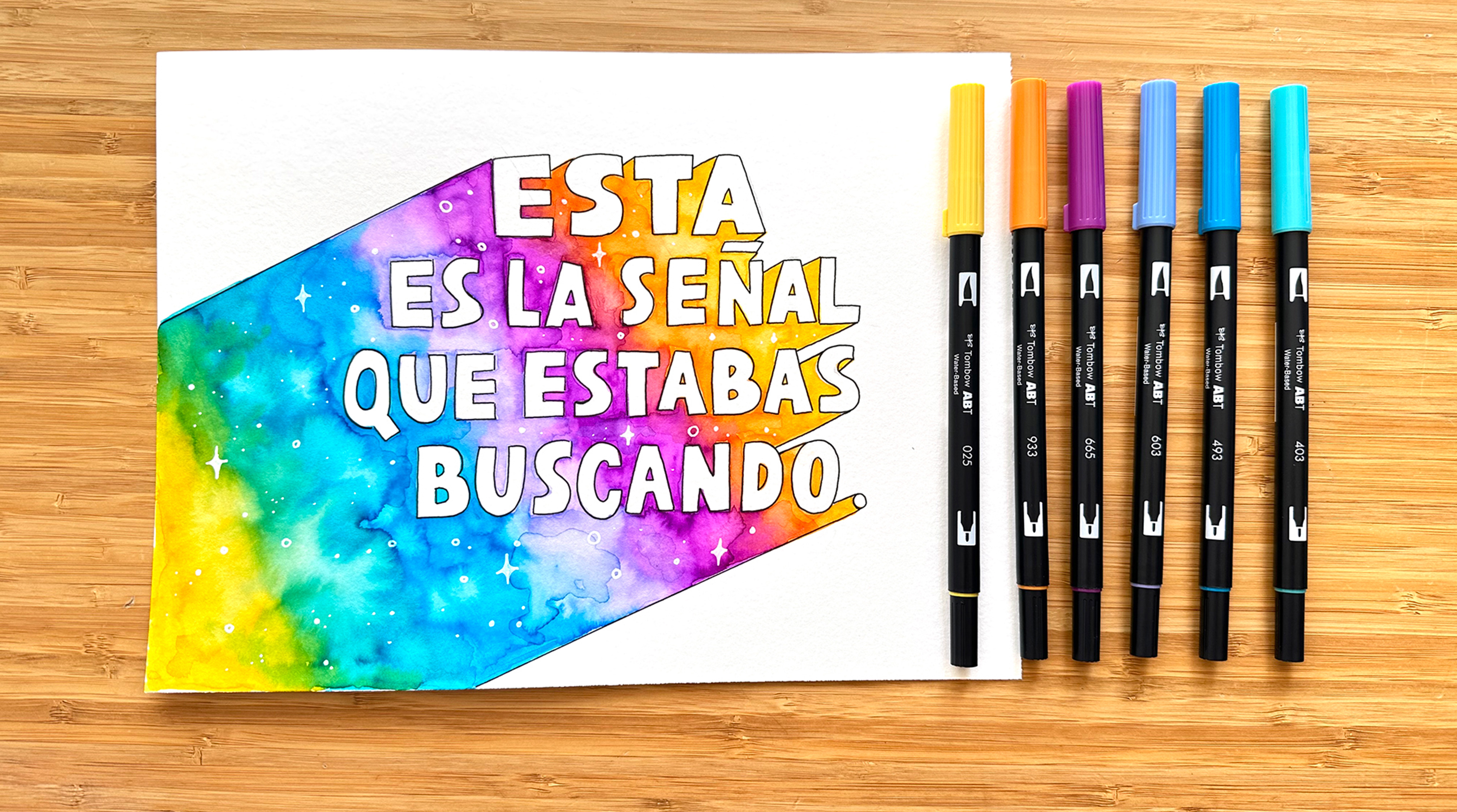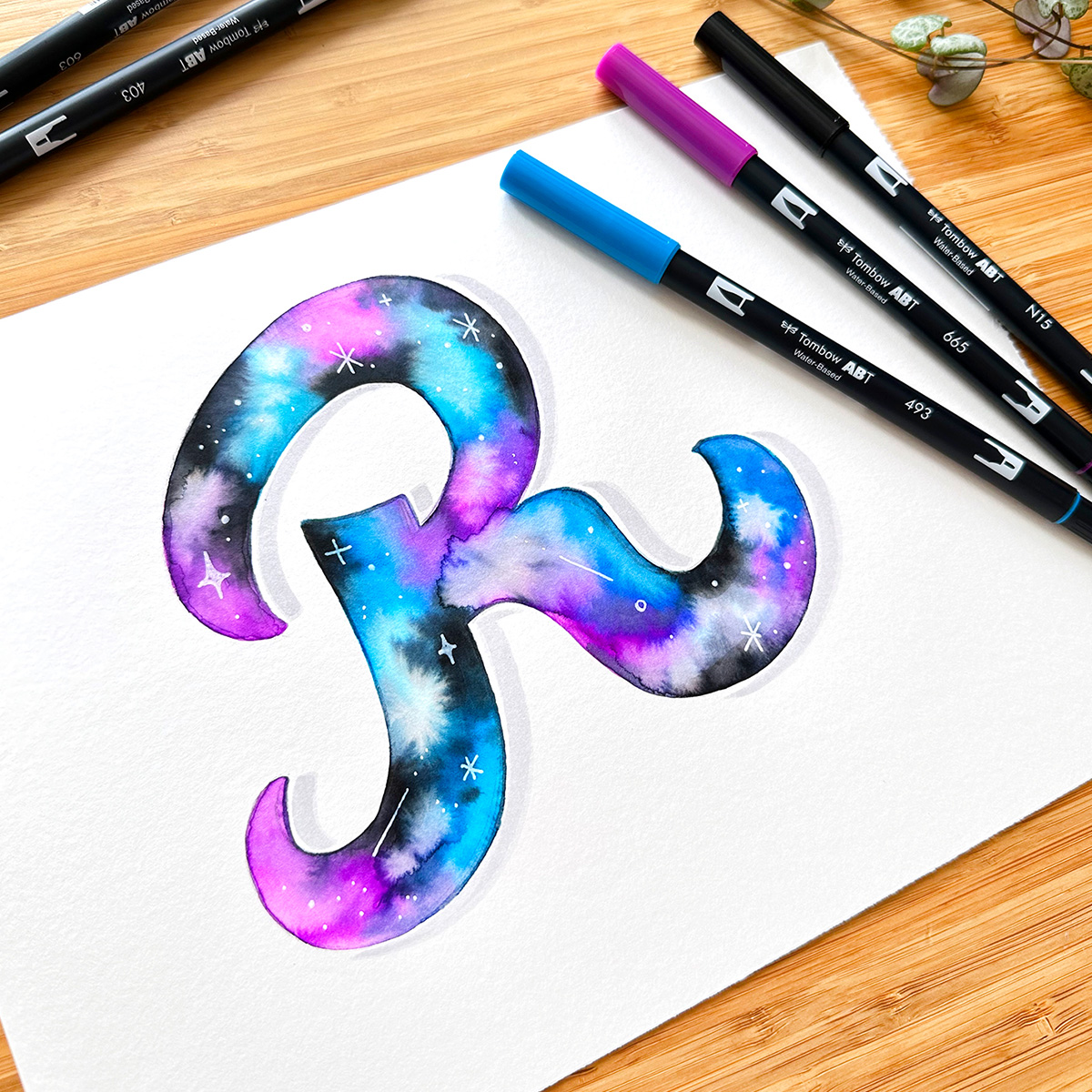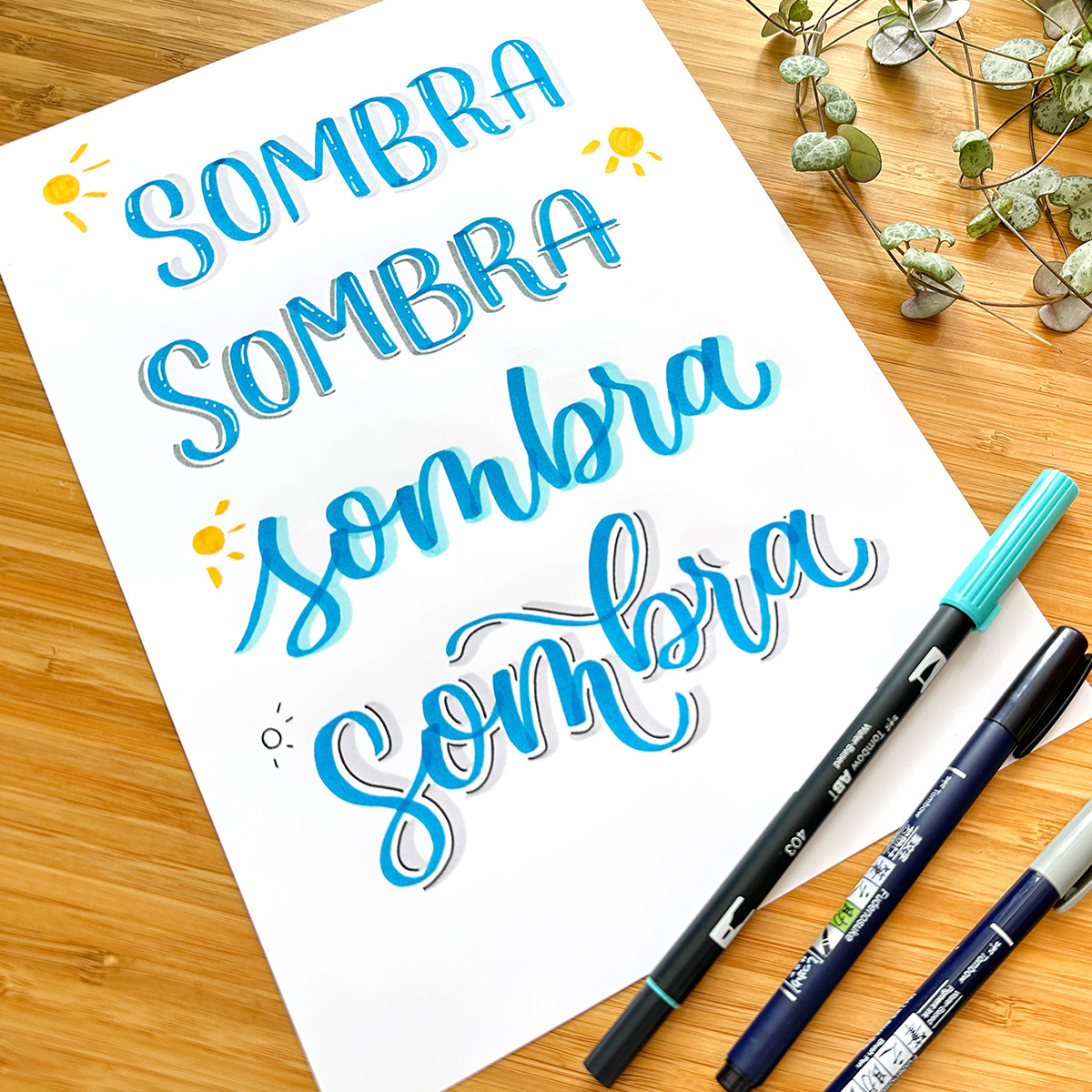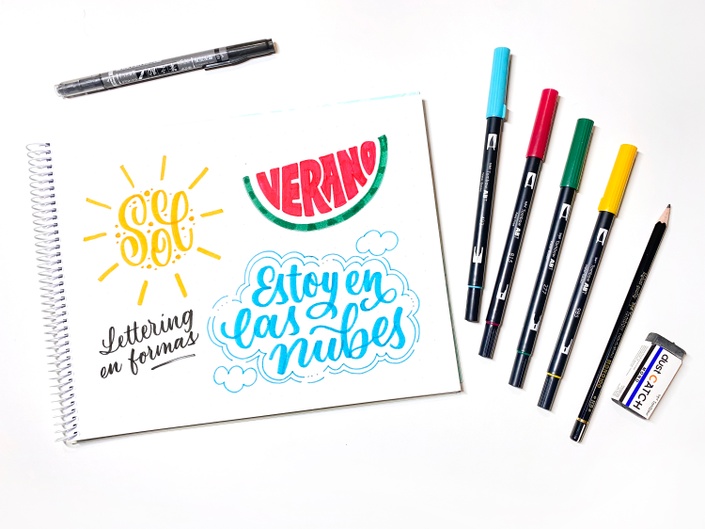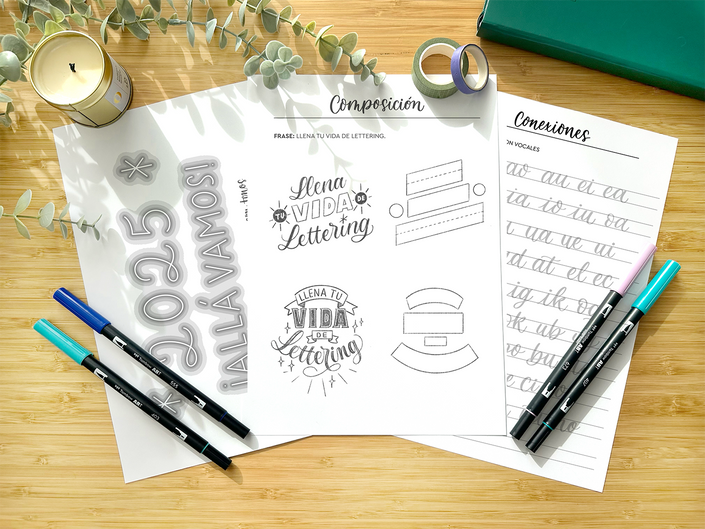
Curso intermedio lettering y caligrafía creativa con brush pen.
Este curso es perfecto tanto si has hecho nuestro curso de iniciación pero también si has aprendido por tu cuenta y ya conoces las bases de la escritura con brush pens o rotuladores de punta flexible.
El objetivo de este curso es que te conviertas en un verdadero artista y le sacas el máximo partido a tus letras.
Capítulo a capítulo, encontrarás explicaciones, consejos para que no se te escape ningún detalle y, además pondrás todo en práctica con los descargables incluidos en el curso.
No hay nada mejor que aprender practicando así que en este curso realizarás desde sencillos ejercicios hasta composiciones con elementos decorativos, sombras, contornos y elementos de colores.
Este curso es perfecto tanto si has hecho nuestro curso de iniciación pero también si has aprendido por tu cuenta y ya conoces las bases de la escritura con brush pens o rotuladores de punta flexible.